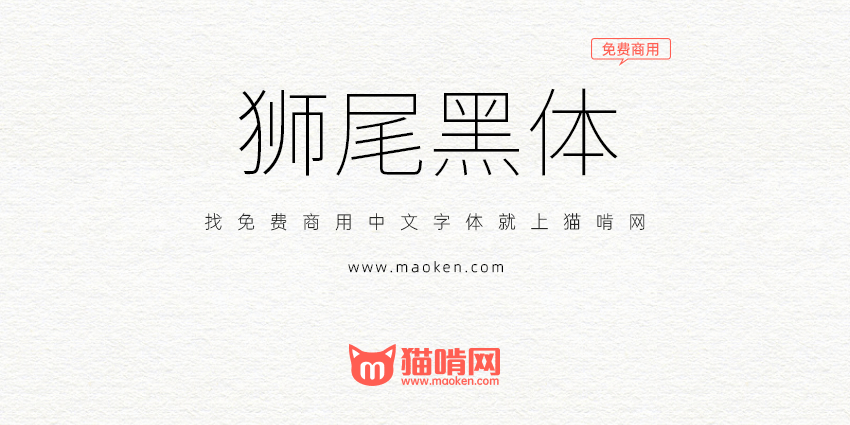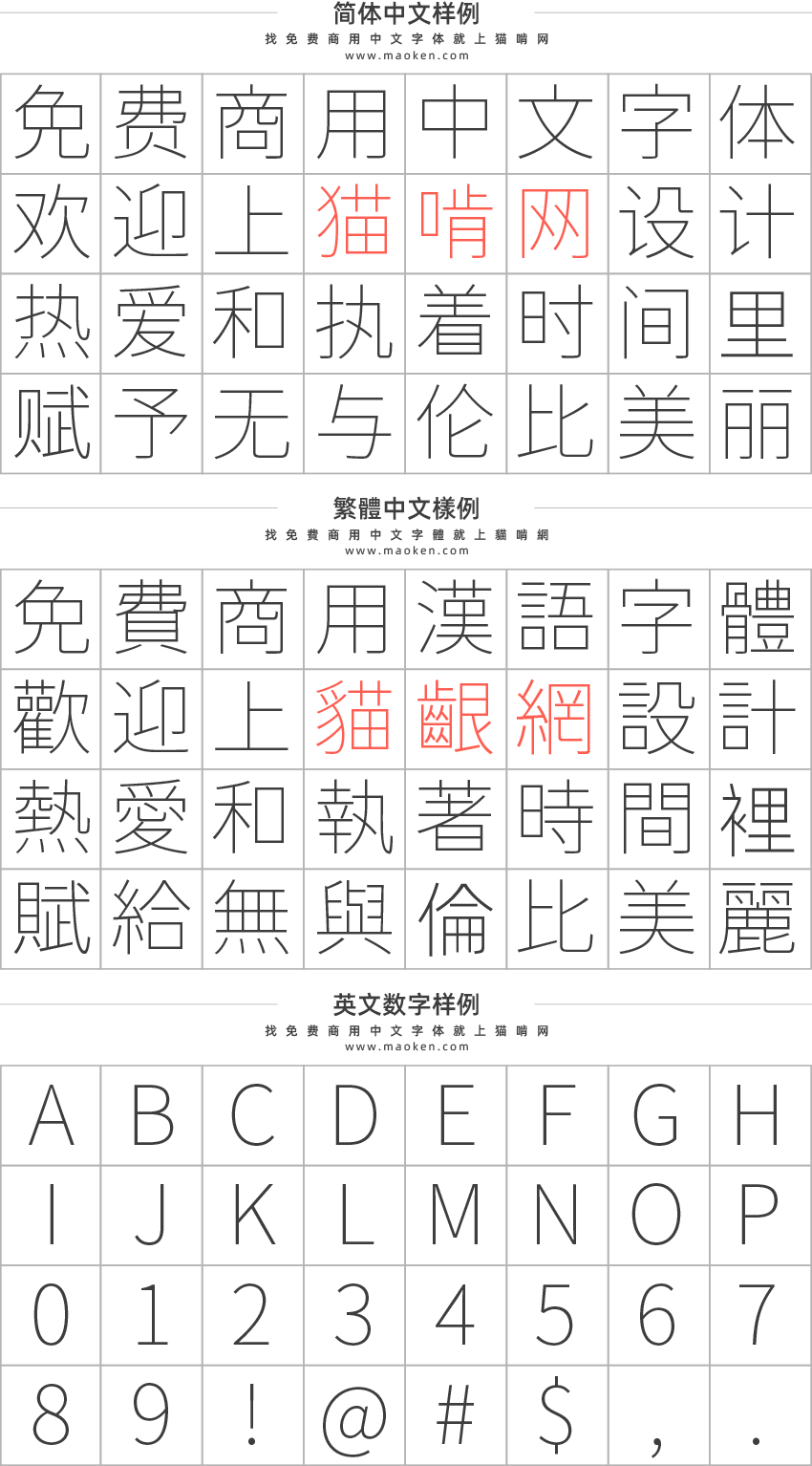
字体作者:Max(中国台湾) | 字体字重:7个 |
台湾设计师Max在见到未来荧黑之后发现,原来思源黑体的“山”和“口”等字型原来是有长脚的,而未来荧黑把思源黑体的长脚给拔除了。于是来了兴趣,也尝试用程序把思源黑体的长脚给拔了,便生成了这款狮尾黑体。
狮尾黑体基于思源黑体的拔脚改造,更加简明现代化的字体。支援简体中文、繁体中文、韩文与日文;提供给大家改造后的思源黑体7种字重。相比于思源黑体,狮尾黑体的造型更加简明现代,版面效果清新轻快。在较重的字重裡,有些脚很难判断该不该拔,就留著了,以避免误拔。
狮尾黑体、思源黑体、未来荧黑的比较,针对有斜边的“山”部,还有“隹”部的尾巴,狮尾黑体表现的比未来荧黑好一点点。详细请看下图的对比。
虽然是下载未来荧黑的CJK TC版本,不过有些笔顺似乎不是台湾用法,像是“每”的母,“讴”的言和区写法比较不一样。像是:集和叶裡“木”的写法也不一样,该分开还是该连在一起。“睁”的眼睫毛方向。“输”的刂。“羽”的开花方式。
ver 2.053(2020/07/23)
- 增加 CHT SC 版本。
ver 2.060(2020/06/24)
- 针对部份常用的文字,调整拔脚的平衡的问题。
ver 2.063(2020/06/14)
- 使用 Noto Sans v2.001,针对辶部及注音符号重新设计。
ver 1.045(2020/06/05)
- 拔掉「闢」的小脚。
- 简化「禺」「禹」系列写法。
ver 1.041(2020/06/04)
- 拔掉中/甲/串系列的小脚。
ver 1.040(2020/06/01)
- 解决有些脚被误拔,例如:遐霞霵劘奜。
ver 1.030(2020/05/21)
- 拔掉「隹」部左下角的小脚。
- 修正2191个字拔脚悬空的问题。(baseline inconsistent)
ver 1.021(2020/04/19)
- 解决异体字对应错误问题,例如:连、诸
ver 1.016(2020/04/13)
- 修正异体字问题,使用aalt lookup
- 使用 TrueType Font
- 增加常用异体字的支援。(manually ‘aalt’ lookup)
ver 1.008(2020/04/08)
修改「傅博㗘㙛圑愽搏溥猼缚馎㬍榑煿牔膊赙磗禣镈䎔䗚䙏糐缚蒪赙𨍭鎛䪙餺䰊髆䶈」系列字体,左下角的脚被误拔的问题。
ver 1.007(2020/03/29)
- 修改「㙛」系列字体,右下角的脚被误拔的问题。
ver 1.005(2020/03/26)
- 修改字型设定值 ROS宣告。
ver 1.004(2020/03/26)
- 狮尾黑体发布第一版。